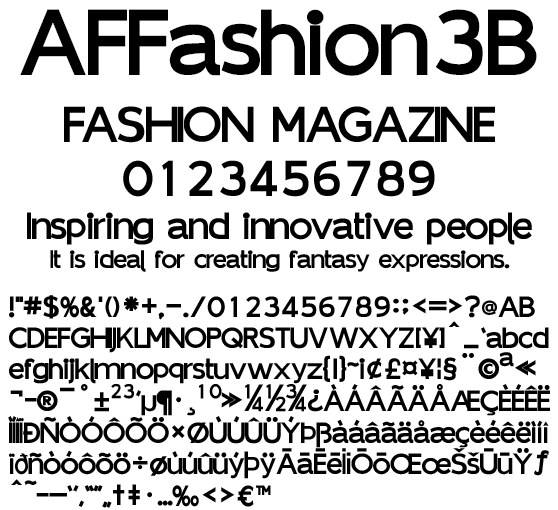
ファッション系 欧文ォント AFFashion3B
AFFashion3B
狭いサイドベアリングに強カーニングでファッション系に最適なボールドウェイトサンセリフ欧文フォントです。ドキュメント、写真、動画テロップ、WebPage などにいかがでしょうか。パンフレット、リーフレット、フライヤー、ファッション系コンテンツに使えるフォントです。日本のローマ字表記で使われる訓令式やヘボン式で扱う Ô や Ō を収録、人名地名へのアプローチもリアルです。